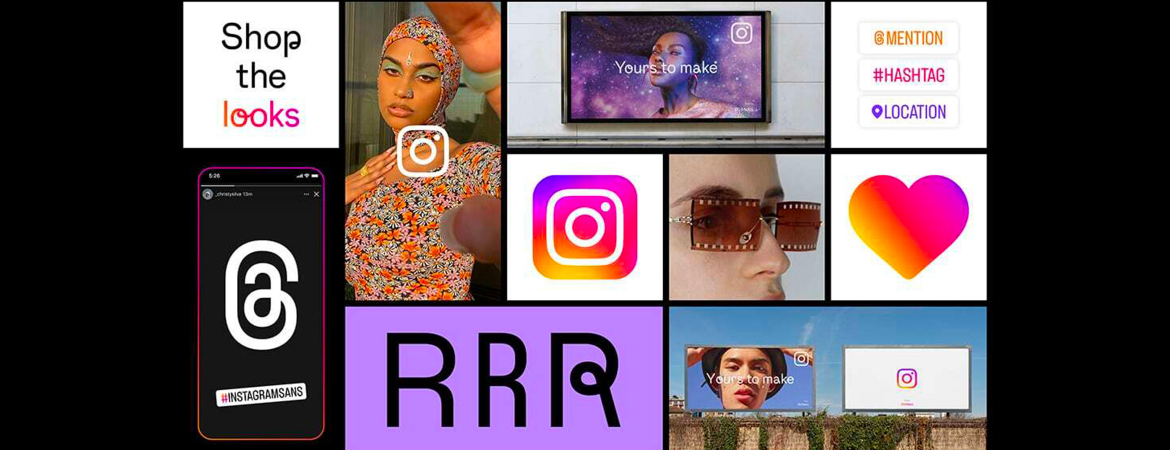
Nouvelle typo, nouvelle identité, nouvelle vie ?
Snapchat n’est pas la seule plateforme à avoir mis en place de nouvelles fonctionnalités récemment. Dans un communiqué paru ce lundi 23 mai, Instagram a annoncé quelques changements sur sa plateforme. Parmi eux, une nouvelle police de caractères – Instagram Sans, inspirée du logo – qui va permettre aux utilisateurs de personnaliser la typo de leurs textes sur la plateforme. Formes carrées, arrondies, épaisses ou fines, vous allez pouvoir laisser libre cours à votre créativité pour vos contenus en tous genres !
Créé à partir de l’ADN d’Instagram, Instagram Sans est une sorte de remix contemporain mêlant les styles grotesques et géométriques. Fabriquées à la main et à l’aide de linguistes, la particularité de cette famille typographique est qu’elle est accessible partout et dans n’importe quelle langue. Ainsi, cette nouveauté permet d’honorer la communauté mondiale des créateurs sur Instagram. Ses polices aussi originales que diversifiées renforceront l’identité d’Instagram.
En complément, la plateforme a mis à jour sa palette de dégradés de couleurs – conçues pour « illuminer » et « inspirer » – ainsi que son système de mise en page. Toujours dans cette idée de simplicité et de création plus « artisanale », Instagram rafraîchit sa plateforme tout en permettant à sa communauté mondiale de se l’approprier.
Attendons de voir ce que les utilisateurs vont penser de cette nouvelle fonctionnalité – les mises à jour n’étant généralement pas très bien accueillies par les communautés, qui doivent perpétuellement se réhabituer aux nouvelles ergonomies.